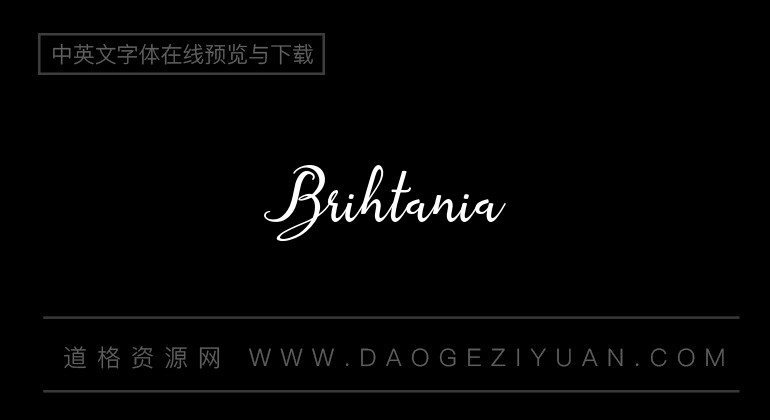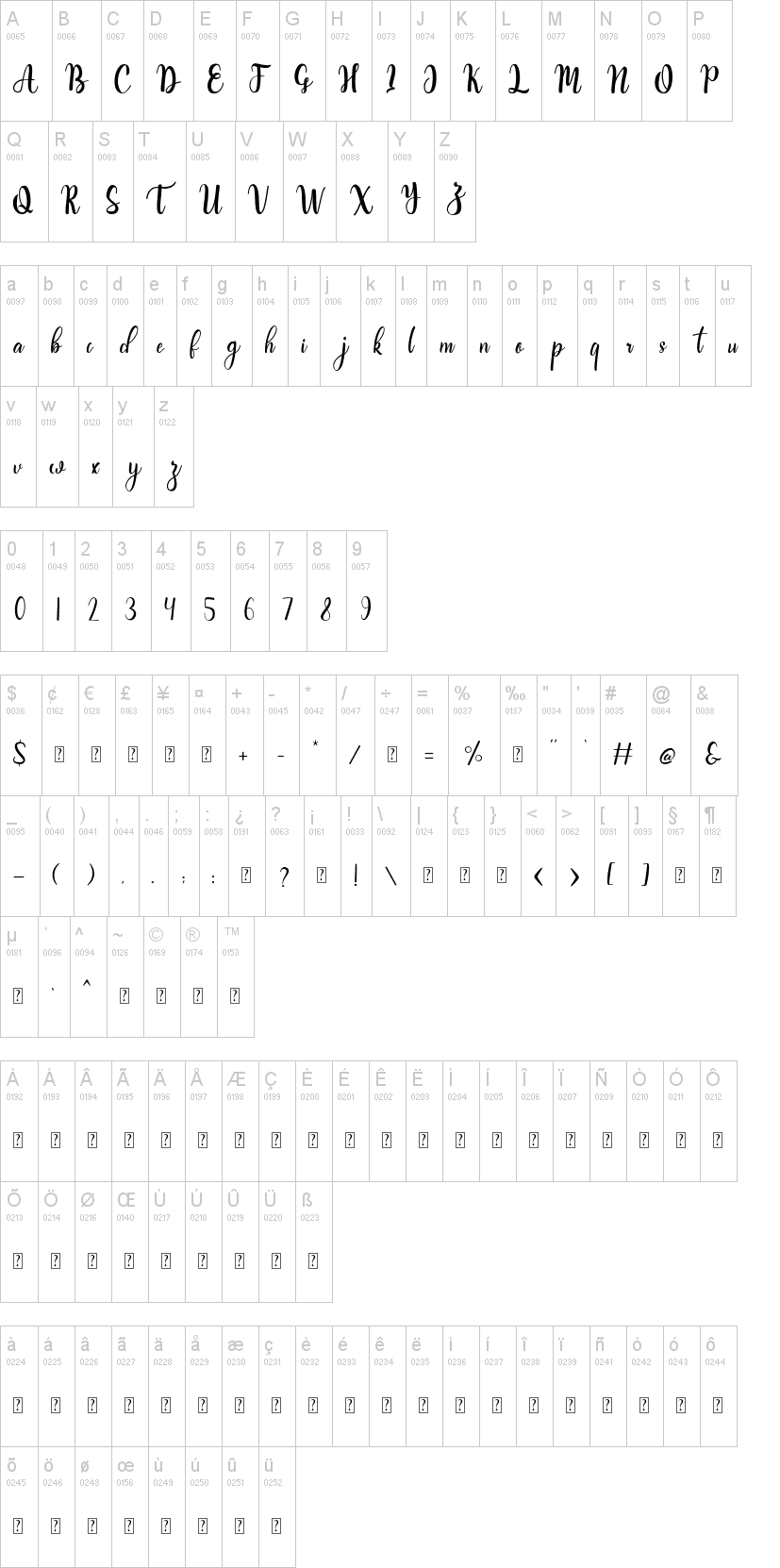
Brihtania 字体是一款拥有英式风格的字体,它采用了经典的英国风格,拥有传统的英式风格,具有细腻的笔画,清晰的字母形状,给人以温暖而又典雅的感觉。它可以用于各种文档,尤其适用于书籍、信件和新闻报道。它也可以用于宣传物品,如海报、宣传单、折页等,以增强宣传效果。内容介绍
Brihtania是一款非常不错的手写艺术字体,具有很好的视觉感,适合于文化类的宣传设计、商业类品牌的广告和产品包装设计以及个性化文字排版等较多场景。